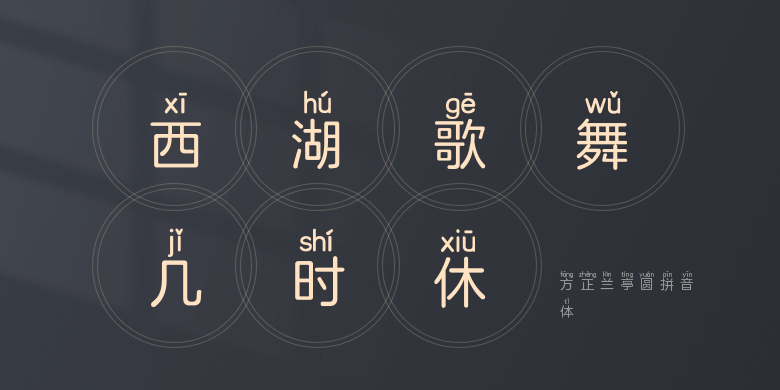
方正兰亭圆拼音体
方正兰亭圆拼音体,这款字体结构工整、笔画清晰,兼顾美观与易读性,适用于标题、正文、海报、包装、LOGO 等多种场景。字形优雅稳定,风格百搭耐看,适配日常排版与创意设计,让文字呈现更舒适、更具质感。方正兰亭圆拼音体一笔一画,皆是细节,以均衡的比例、流畅的线条打造舒适视觉体验,字形端正大气,风格简约现代。无论是商业设计、品牌宣传还是日常排版,都能轻松驾驭,让文字更有格调与力量。方正兰亭圆拼音体字体下载。